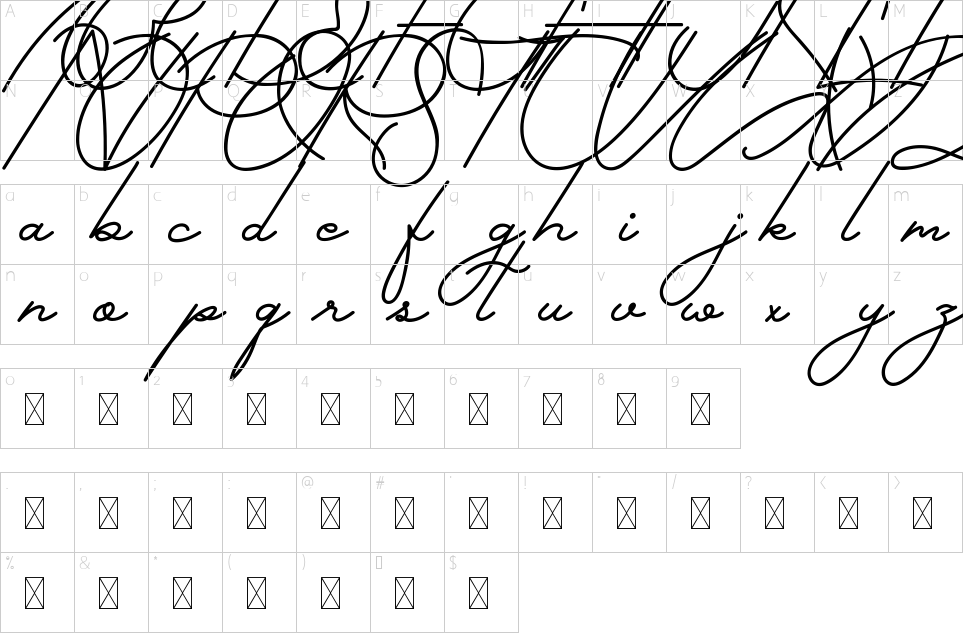
A Gallery Dwiarna é uma elegante e delicada fonte gráfica que combina perfeitamente para trabalhos profissionais e projetos pessoais. Desenvolvida pelo designer não identificado nihstudio, esta fonte vem com um amplo leque de usos, desde o design editorial até a criação de logotipos e materiais digitais. Com seu design minimalista e sofisticado, Gallery Dwiarna é uma escolha inteligente para quem procura uma fonte que não só se destaca, mas também se integra harmoniosamente em qualquer projeto. Recentemente baixada 15.249 vezes pelo público global, a Gallery Dwiarna atende à necessidade de adicionar um toque único e estiloso aos seus projetos digitais. Sem dúvidas uma opção inconfundível para designers que valorizam tanto o resultado quanto a aparência do trabalho final.